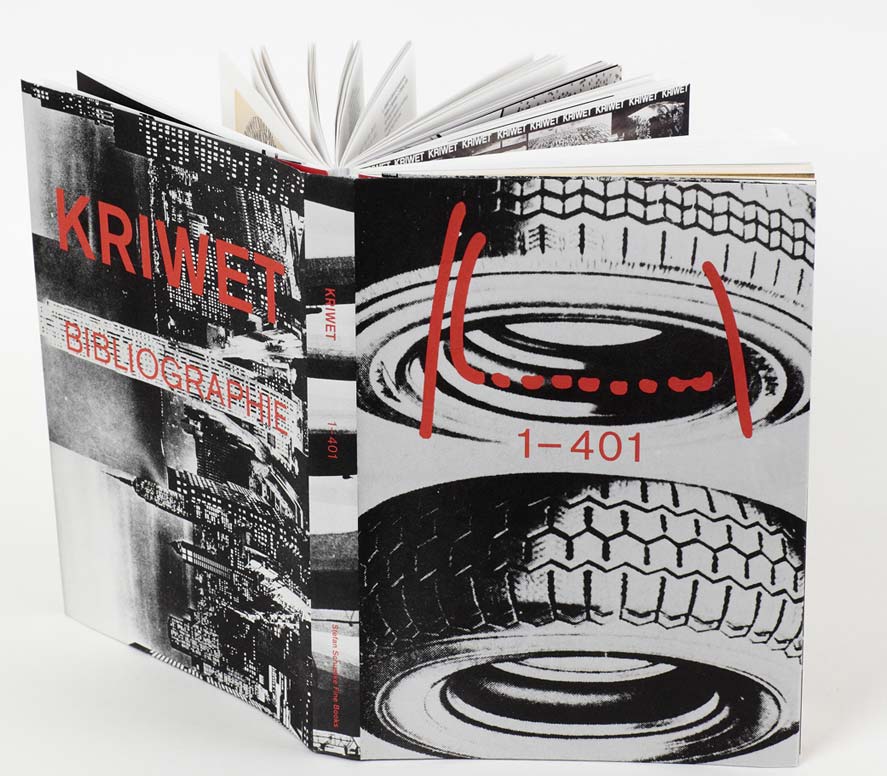
Der 1942 in Düsseldorf geborene Ferdinand Kriwet gilt als ein Pionier der Medienkunst. Bereits in den frühen 1960er Jahren widmete er sich in Ausstellungen, Bühnenauftritten und Hörspielen unseren Sehgewohnheiten, die er durch die Reizüberflutung der Massenmedien beeinflusst sah. Dazu analysierte er die Sprache von Fernsehen, Werbung und Fotografie. Nun dokumentiert ein liebevoll ausgestattetes Buch das Kriwet-Gesamtwerk. Dazu startet am 7. September bei Stefan Schuelke Fine Books in Köln eine dreiwöchige Ausstellung.
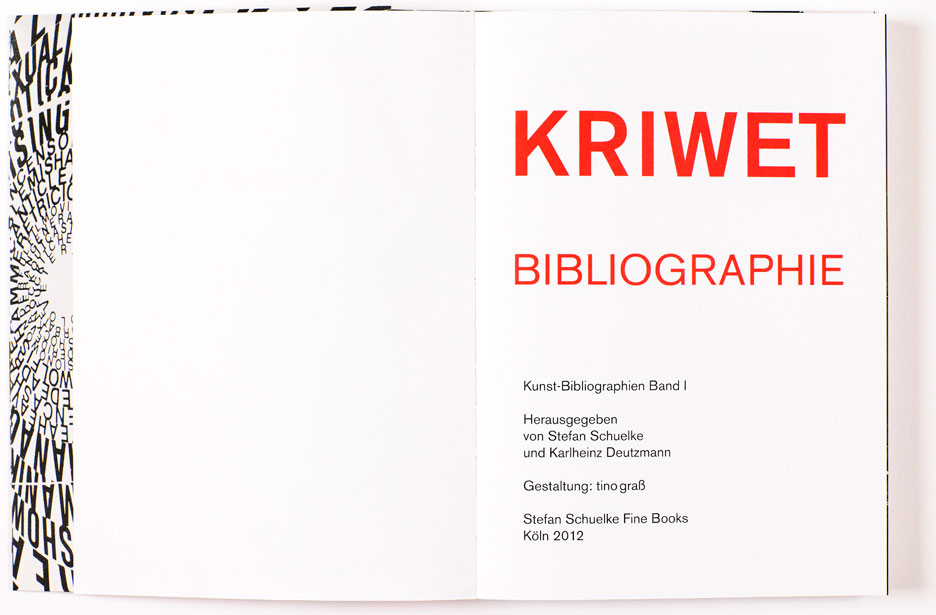
Kriwets künstlerische Schwerpunkte liegen in den Bereichen Hörspiel, visuelle und konkrete Poesie, interdisziplinäre Sprachkommunikation und – jetzt wird es für die Leser des Fontblog interessant – Sehtexte. Sein Interesse gilt einer Sprache, die für ihn nicht nur Wort, sondern auch Bild ist. Und so bezeichnet er sich selbst auch gerne als »visueller Poet«.
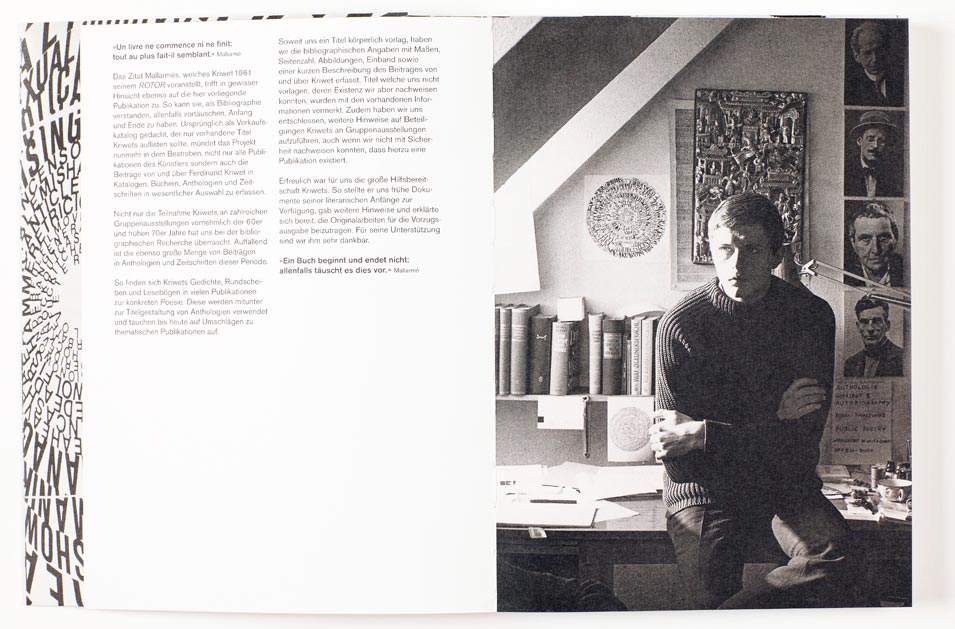
»Ein Buch beginnt und endet nicht: allenfalls täuscht es dies vor.« Mit diesem Zitat von Mallarmé beginnt eines der bedeutendsten Werke von Ferdinand Kriwets, das 1961 bei DuMont erschienen Rotor-Heft. Da war Kriwet gerade 19 Jahre alt. Rotor ist ein Fließtext, ohne Großbuchstaben, ohne Punkt und Komma. Es war die Zeit, in der man den Roman als Kunstform für tot erklärte. Die Syntax wurde aus den Fesseln der Semantik befreit. Sehen und Schreiben, Sehen und Lesen wurden eins.
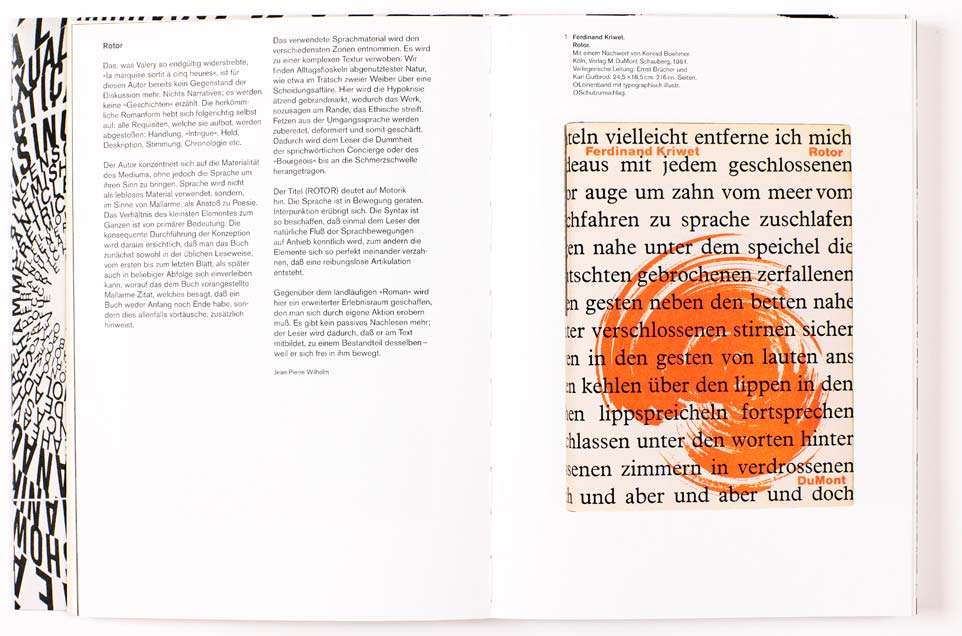
Kriwet auffälligste Erfindung sind seine poetisch-programmatischen Rundscheiben, entstanden überwiegend zwischen 1961 und 1963. Diese Schriftspiralen, seitenverkehrt, gespiegelt, gebrochen und kreisförmig angelegt, werden zu seinem Markenzeichen. Wortschöpfungen wie NATUREVOLUTIONUTOPIABENTEUR, HOMODELIGHT oder PHALLICUSHY erregten auf Plakatwänden im öffentlichen Raum das Interesse von Kunstwelt und Passanten. Auf Leinwand, gestanzt in Blech, als aufblasbares Luftkissen und auf Klarsichtfolie wurden sie in Galerien ausgestellt.
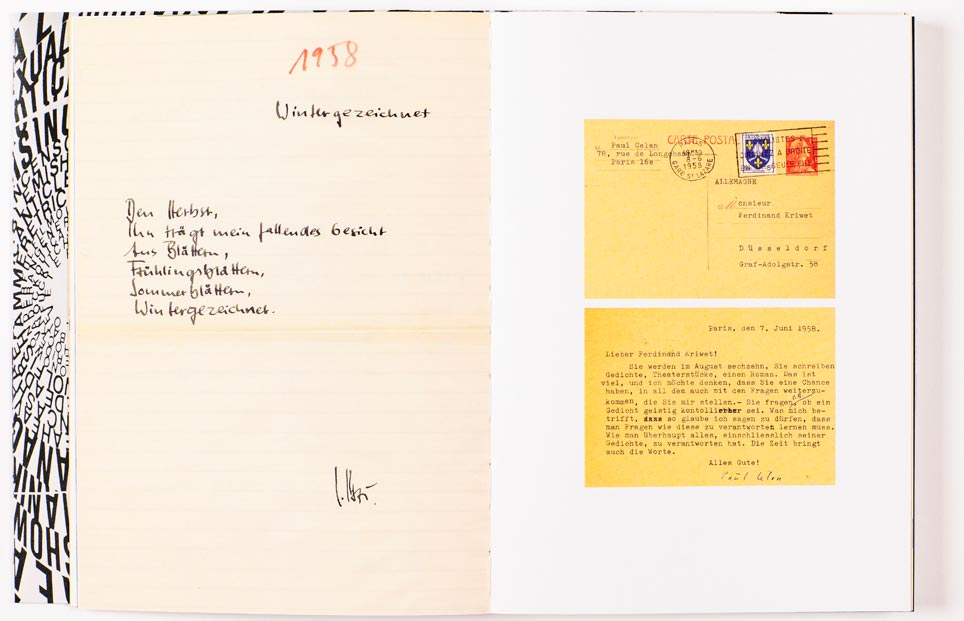
Neben Neonschriften und Wandbemalungen gestaltete der in Düsseldorf geborene Künstler in den nachfolgenden Jahren etliche Kunst-am-Bau-Projekte. Überdies produzierte er eine große Zahl von Rundfunkbeiträgen. Besucher der DuMont-Verlagszentrale in Köln begegnen Ferdinand Kriwets Arbeiten überall: Von ihm stammen die Motive auf den Glastüren im gesamten Verlagsgebäude.
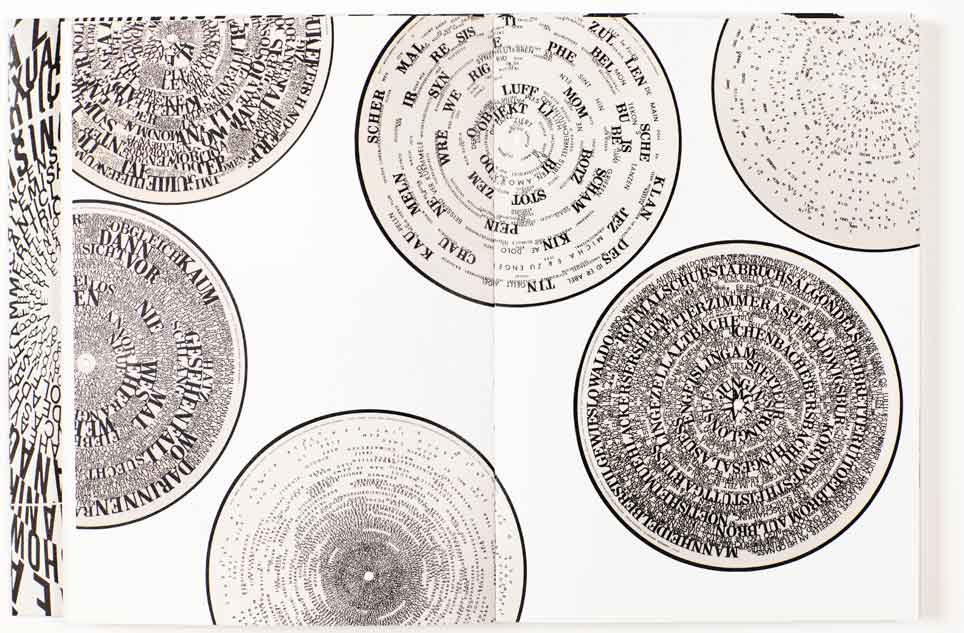
Nach seinem »Rückzug« aus der Kunstszene Mitte der 1970er Jahre beginnt Kriwet 2004 erneut künstlerisch zu arbeiten. 2011 widmete ihm die Kunsthalle Düsseldorf eine große Retrospektive.
Kriwets Gedichte, Rundscheiben und Lesebögen finden sich in vielen Schriften zur konkreten Poesie. Sie wurden zur Titelgestaltung von wichtigen Anthologien verwendet und tauchen bis heute auf Umschlägen zu thematischen Publikationen auf. Die nun erschienene, liebevoll recherchierte und von Tino Graß gestaltete Kriwet Bibliografie dokumentiert zum ersten mal alle Publikationen und Tonträger des Künstlers, seine Einzel- und Gruppenausstellungen, sowie Beiträge von und über Kriwet in Büchern, Anthologien und Zeitschriften. Gezeigt werden zudem bisher unveröffentlichte Manuskripte, Briefverkehr und Zeugnisse seiner frühen literarischen Arbeit.